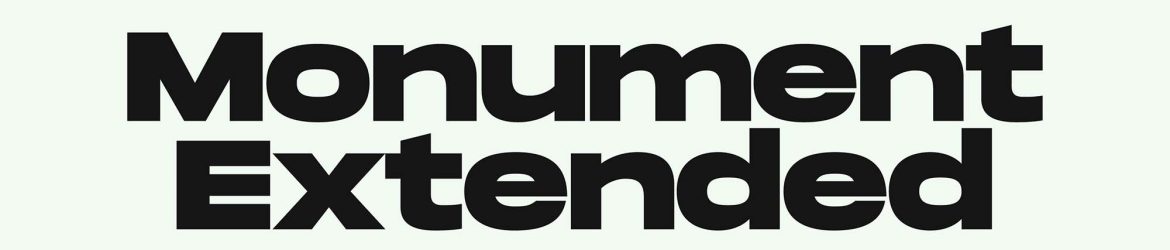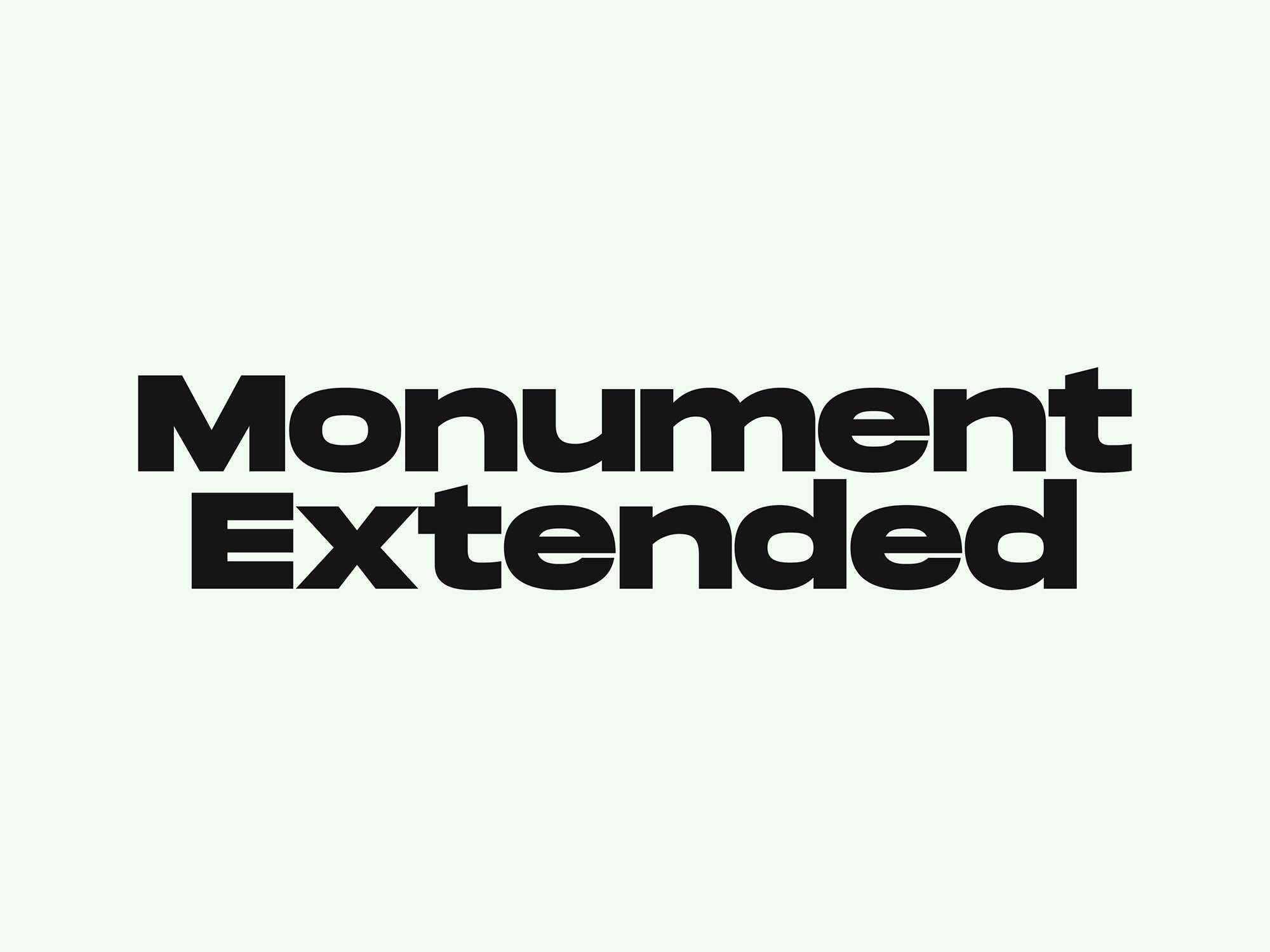
Monument Extended Font
Aqui está uma descrição em português para a página de download do recurso gráfico ‘Monument Extended Font’, no estilo solicitado: Um monumento é uma estrutura construída para honrar um evento ou pessoa especial, e agora você tem à sua disposição um novo recurso gráfico que vai transformar seus projetos. Este é o Monument Extended Font, um projeto de Pangram que traz uma estética única e uma grande versatilidade. Este recurso gráfico é perfeito para quem deseja dar um toque único em seus projetos, seja em design de sites, gráficos, logotipos ou até mesmo em aplicativos. Com o Monument Extended Font da Pangram Pangram, você pode explorar um estilo único que vai diferenciar seus projetos de forma atraente. Este recurso gráfico, com sua ampla gama de uso, é uma opção ideal para designers e criativos que desejam tornar suas criações mais impressionantes. Ele traz um toque de elegância e personalização para qualquer projeto onde seja aplicado, transformando-o em algo inovador e memorável.